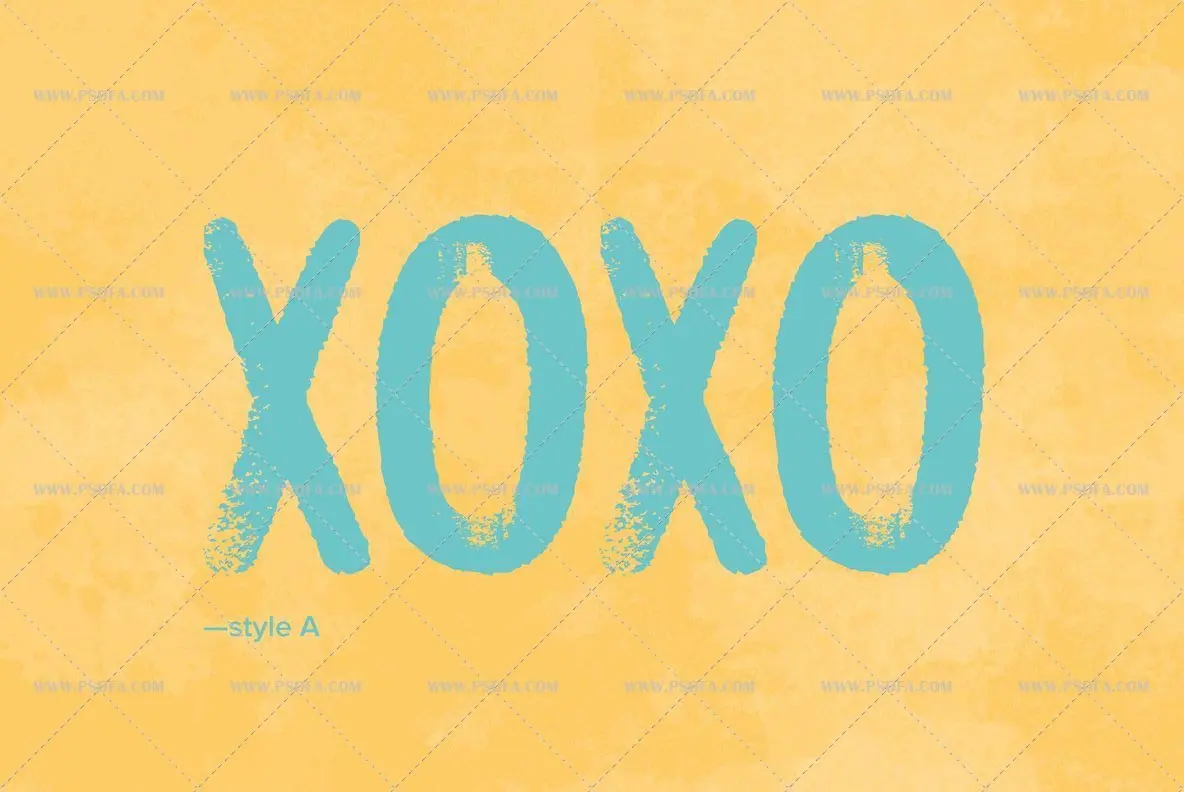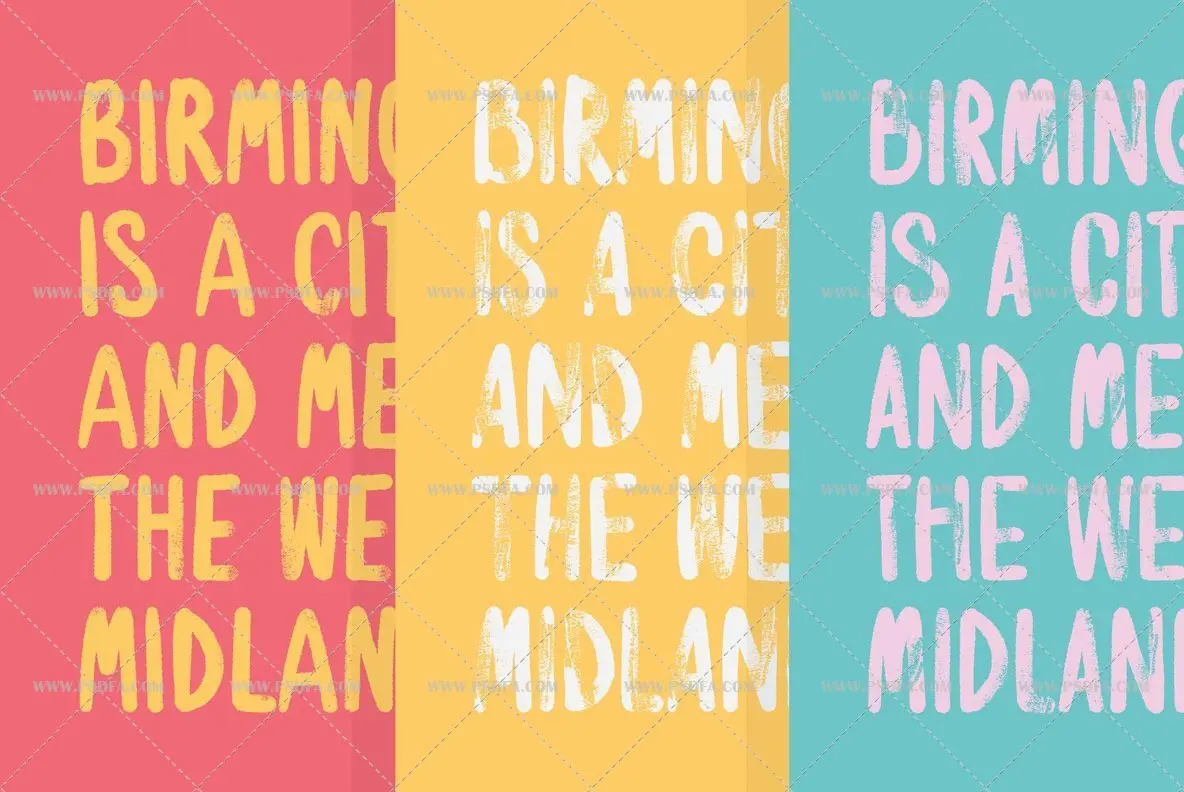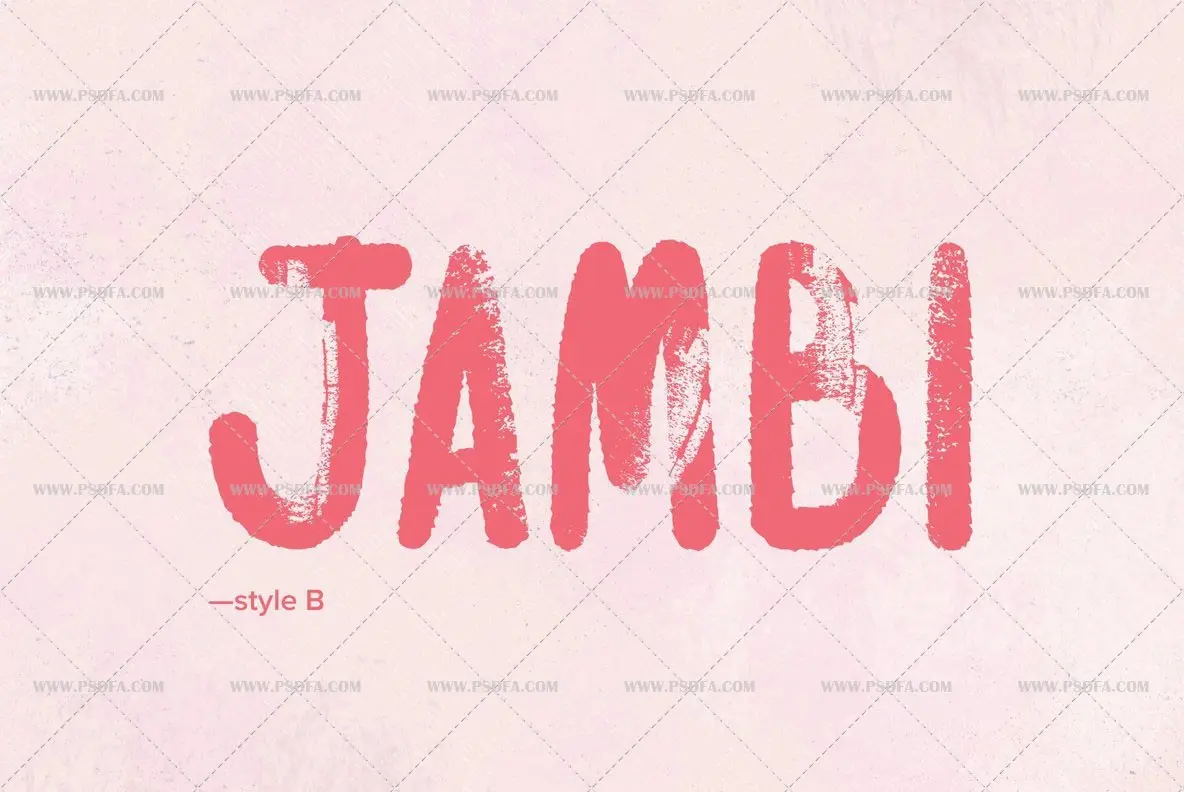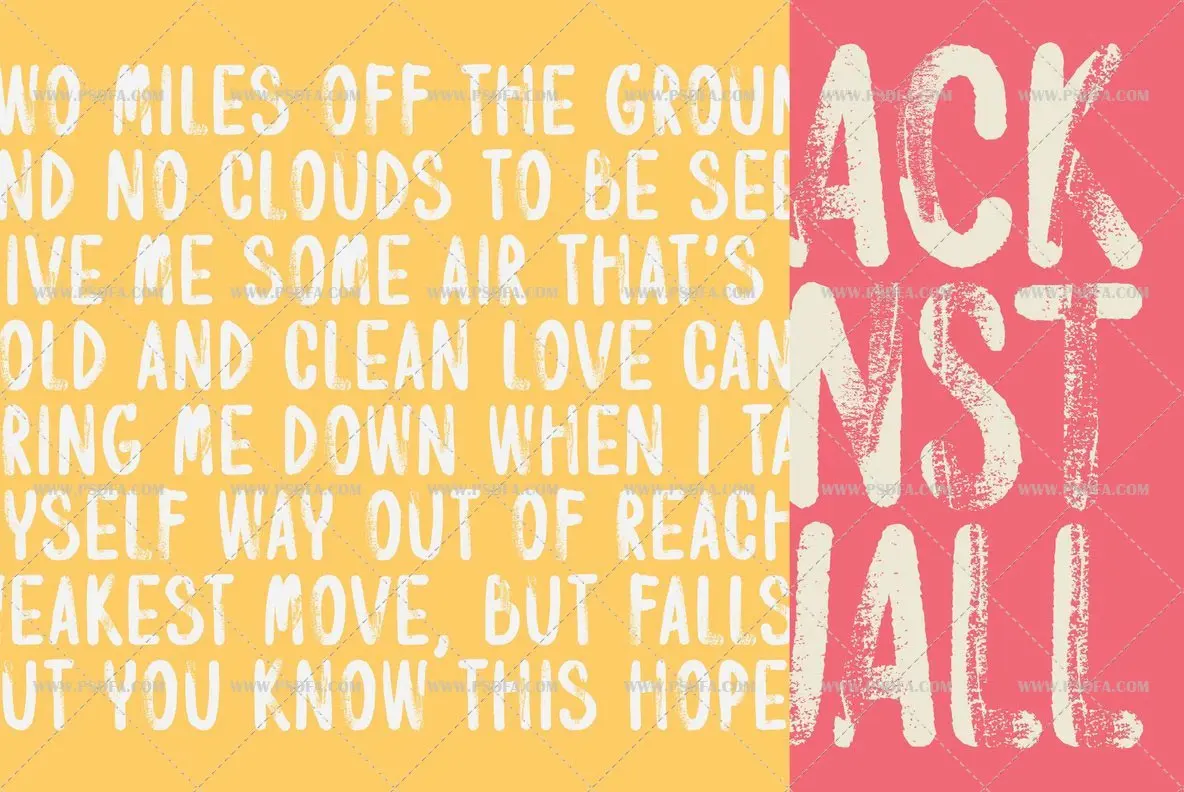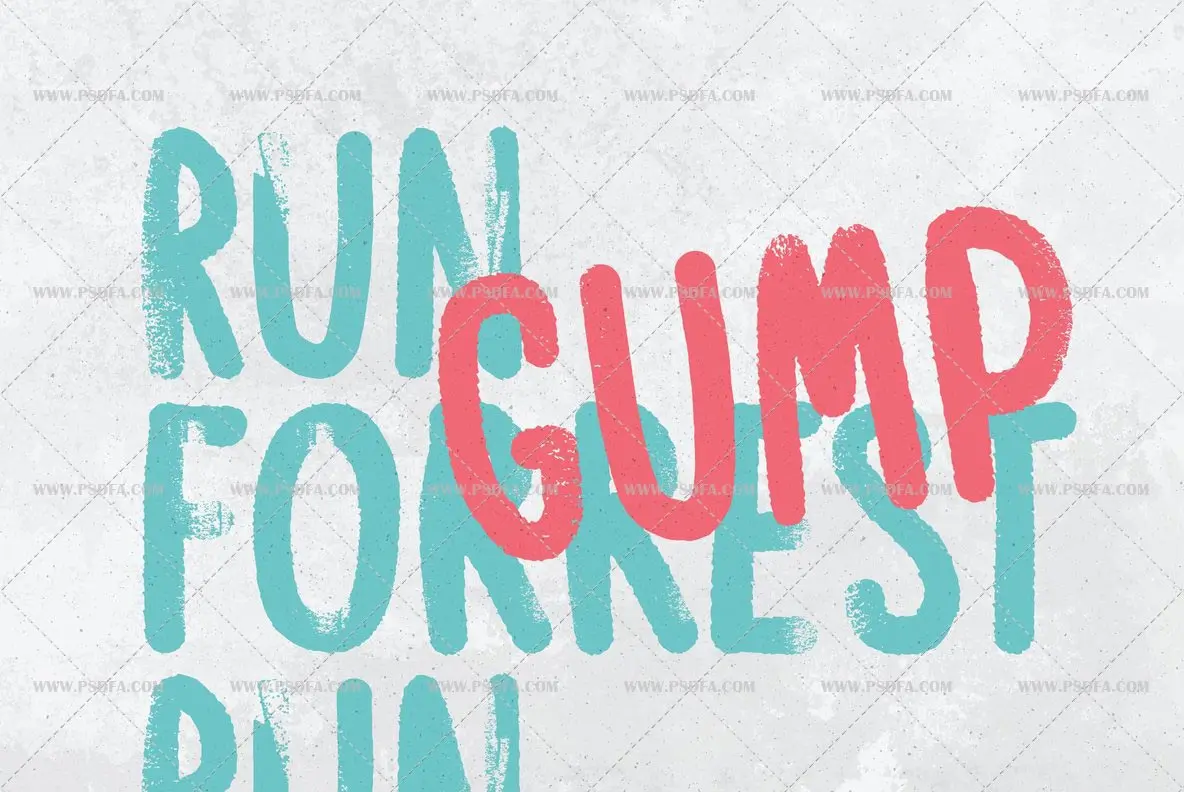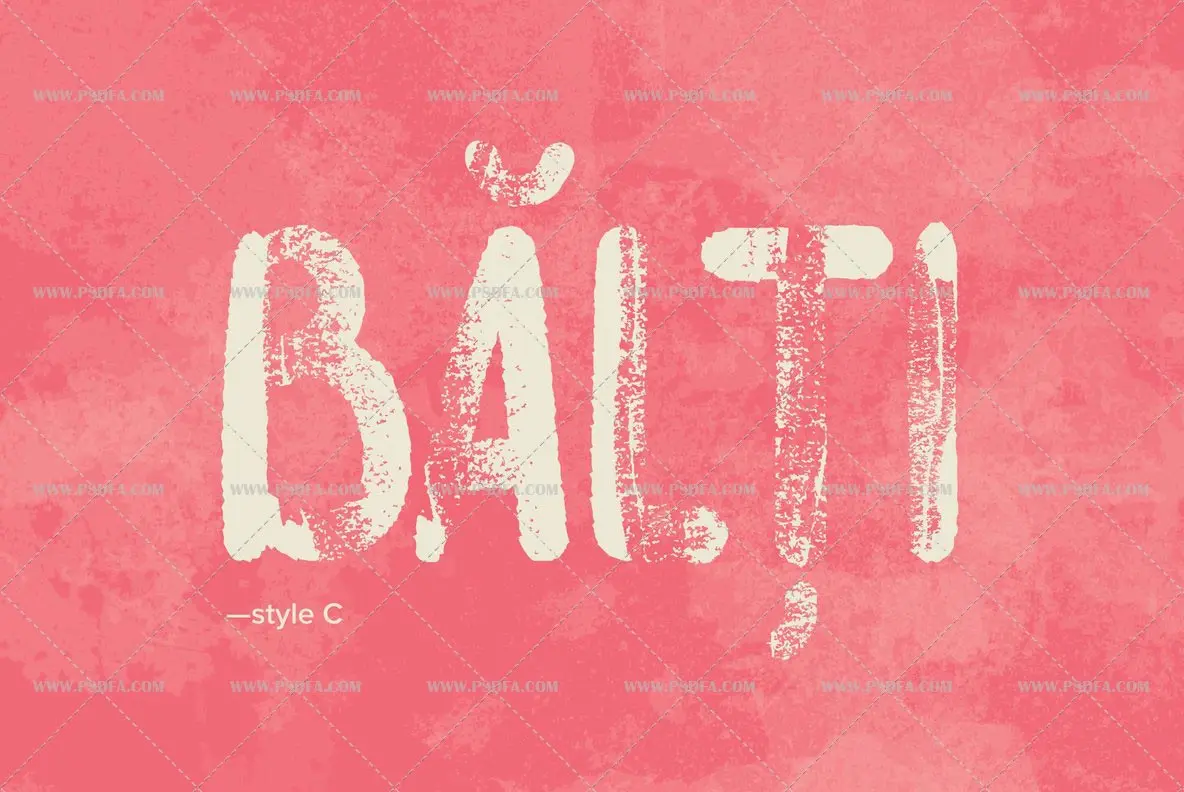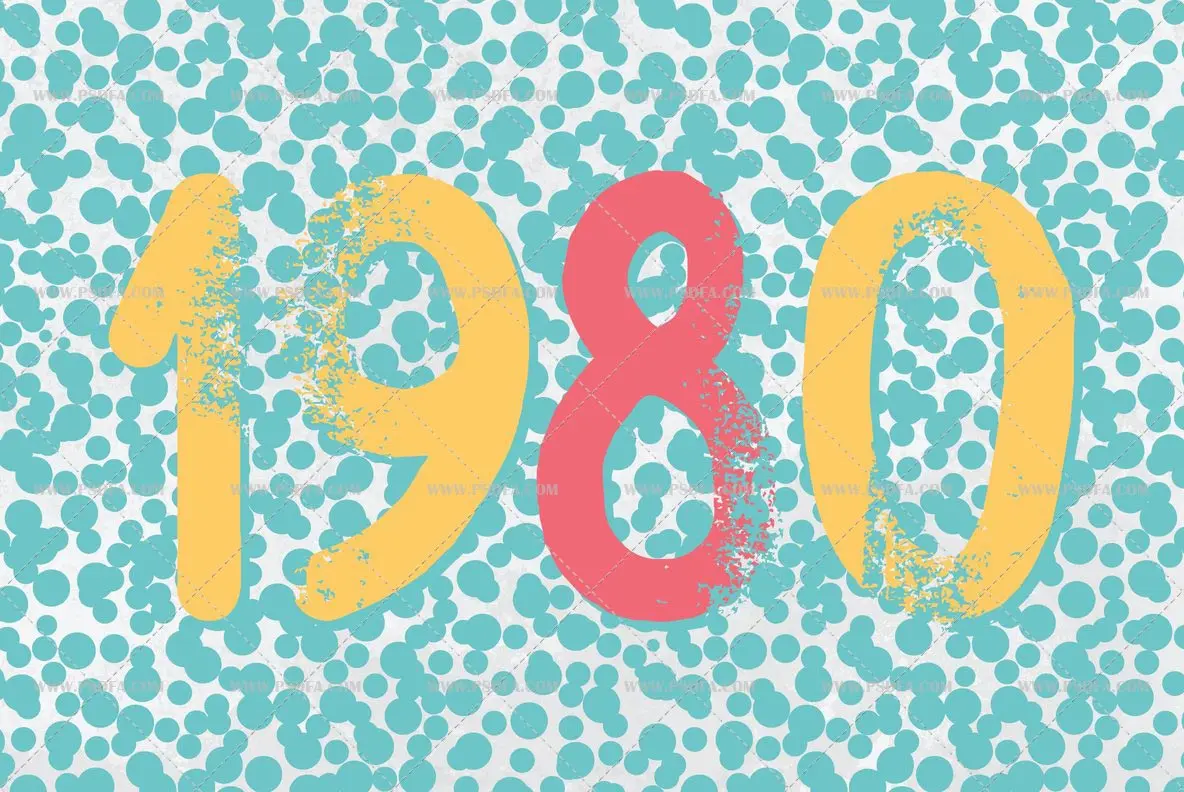
فونت انگلیسی YWFT Watermelon مناسب برای طراحی گرافیکی
فونت انگلیسی YWFT Watermelon
در این مطلب برای شما طراحان و گرافیستان عزیز فونت انگلیسی YWFT Watermelon که مناسب جهت طراحی می باشد را قرار داده ایم. این فونت که با دو فرمت OTF و TTF در فایل فشرده موجود است دارای سه سبک طرح و استایل قلمویی می باشد یعنی پس از خارج کردن فایل فشرده شاهد 6 فایل که سه تا با فرمت OTF و سه تای دیگر با فرمت TTF می باشد هستید. از نظر کیفیت نیز فونت ها دارای کیفیتی بالا می باشند که پس از نصب بر روی سیستم خود می توانید در تمام نرم افزارهای گرافیکی و ویرایش متن از آن ها استفاده کنید. از فونت YWFT Watermelon می توان در طراحی انواع پوستر ، طراحی ظروف یک بار مصرف ، طراحی جعبه هدیه ، طراحی انواع کارت های دعوت ، کارت پستال ، کارت هدیه ، طراحی بسته بندی محصولات ، طراحی پاکت و نایلون خرید و ده ها ایده دیگر استفاده نمود. پیش نمایش این فونت زیبا را می توانید در تصاویر زیر مشاهده فرمائید.
- دارای سه سبک استایل